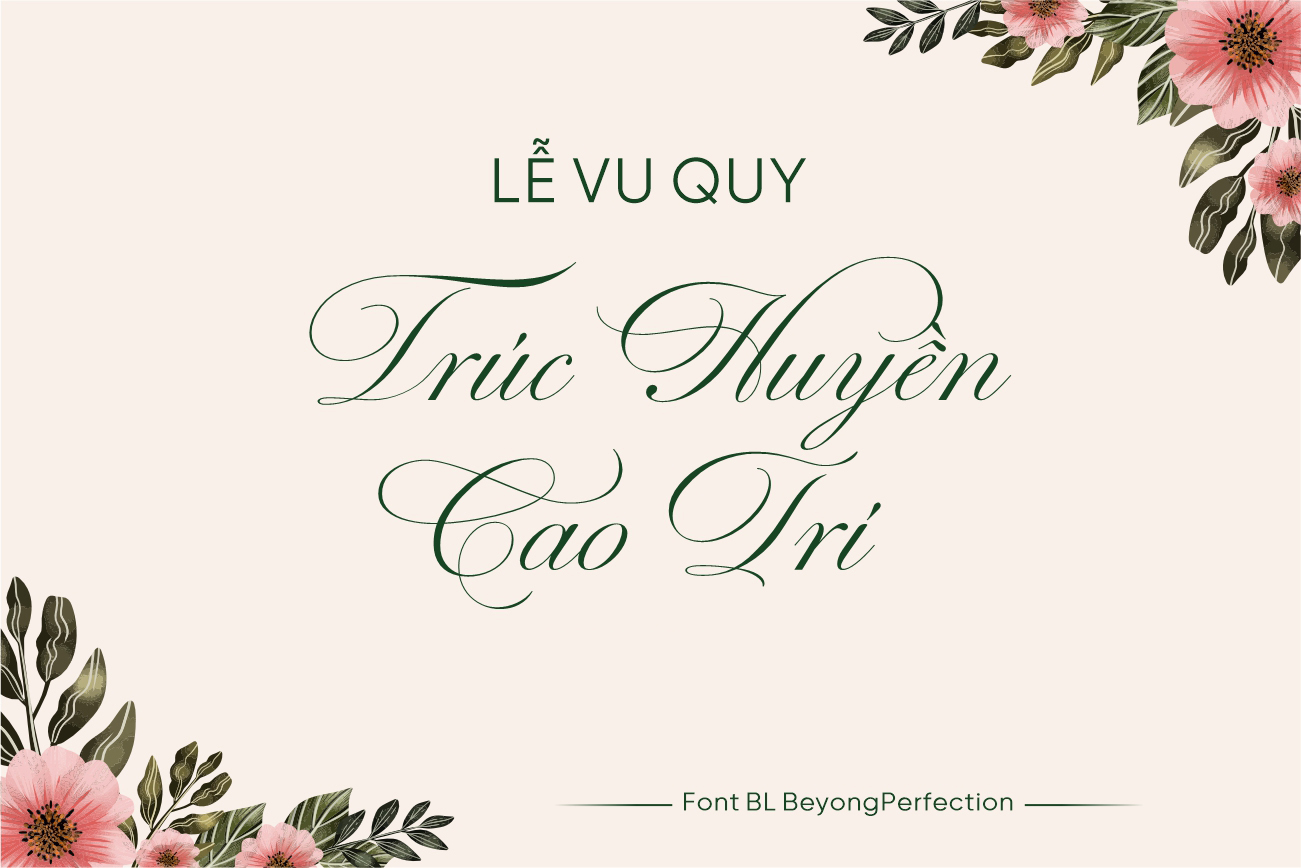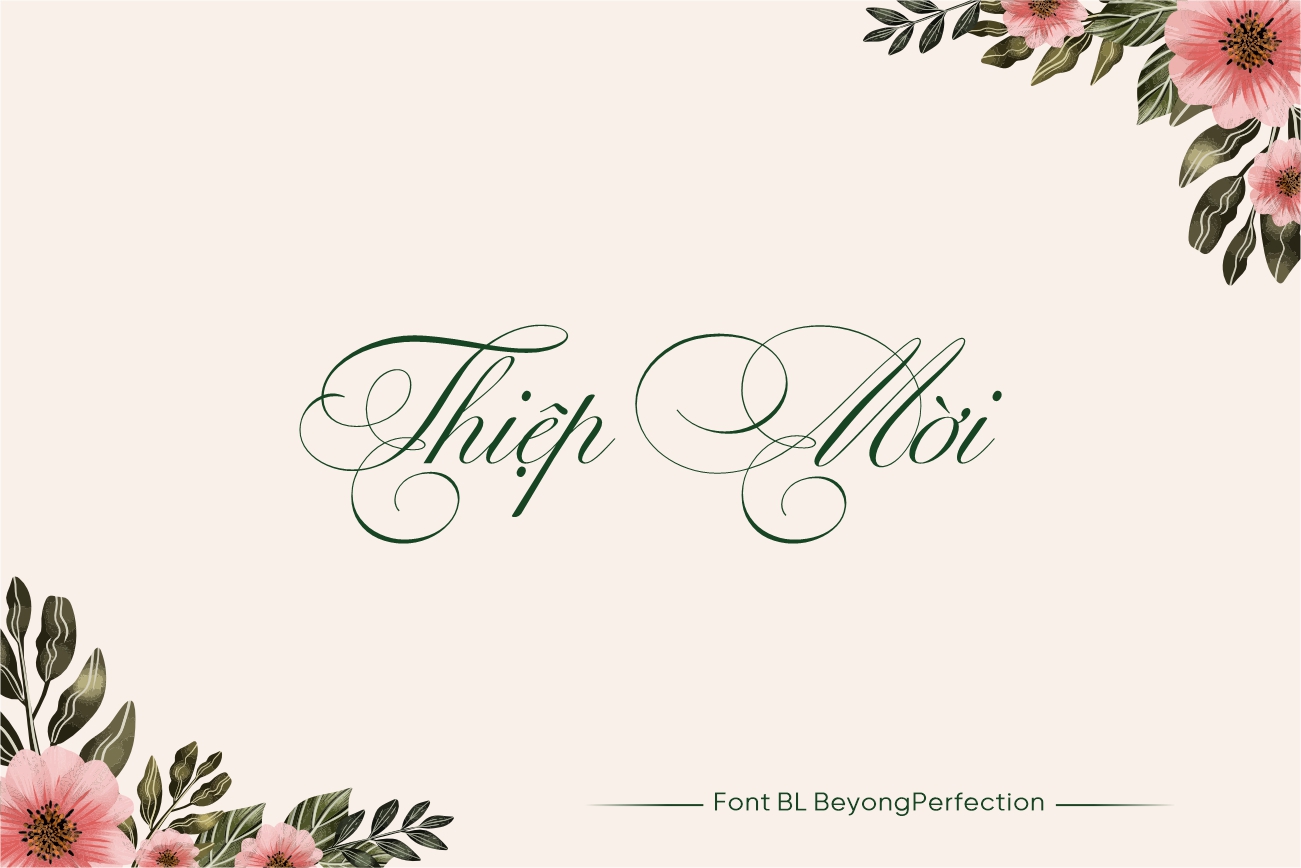
Phông chữ nét mảnh cho thiệp cưới BL Beyond Perfection Việt Hóa
BL Beyond Perfection là phiên bản Việt hóa từ bộ font Beyond Perfection do Hendra Pratama thiết kế, mang đậm tinh thần nghệ thuật của chữ viết tay cao cấp và cảm xúc lãng mạn. Ngay từ cái nhìn đầu tiên, bộ chữ tạo ấn tượng bởi sự mềm mại, uyển chuyển và tinh tế, thể hiện rõ nét của một font script hiện đại kết hợp calligraphy. Team BL đã Việt hóa cẩn thận, tối ưu hệ thống dấu tiếng Việt để từng ký tự liền mạch, hài hòa và giữ được trọn vẹn vẻ đẹp nguyên bản của font gốc. Nhờ đó, BL Beyond Perfection không chỉ đẹp về mặt thị giác mà còn dễ ứng dụng trong các dự án thiết kế tại Việt Nam.
Về kiểu dáng, BL Beyond Perfection sở hữu những đường nét uốn lượn tự nhiên, mềm mại và có nhịp điệu rõ ràng, tạo cảm giác uyển chuyển như bút mực đang lướt nhẹ trên giấy. Các nét chữ được xử lý với độ dày mỏng linh hoạt, mang lại chiều sâu và cảm xúc cho từng con chữ. Sự kết hợp giữa cấu trúc script hiện đại và tinh thần calligraphy cổ điển giúp font vừa mang hơi thở đương đại, vừa giữ được vẻ sang trọng và nghệ thuật. Khi sử dụng trong thiết kế, bộ chữ dễ dàng trở thành điểm nhấn, làm cho nội dung trở nên nổi bật mà không bị rối hay quá phô trương.
BL Beyond Perfection đặc biệt phù hợp với những thiết kế cần truyền tải cảm xúc và tính thẩm mỹ cao. Từ thiệp cưới, thiệp mời, thiệp chúc mừng, logo thương hiệu cá nhân, thời trang, mỹ phẩm cho đến poster nghệ thuật hay nội dung truyền thông trên mạng xã hội, font đều phát huy tốt khả năng gợi cảm xúc. Tổng thể kiểu chữ gợi cảm giác lãng mạn và nghệ thuật, giúp người xem cảm nhận được sự tinh tế, nhẹ nhàng và giàu chất thơ trong từng dòng chữ. Đây là lựa chọn lý tưởng cho những dự án cần sự mềm mại nhưng vẫn giữ được nét chuyên nghiệp và chỉn chu.
Nguồn gốc của Beyond Perfection xuất phát từ cảm hứng về sự hoàn mỹ trong nghệ thuật chữ viết tay, nơi từng chi tiết nhỏ đều góp phần tạo nên cảm xúc trọn vẹn. Khi được Team BL Việt hóa thành BL Beyond Perfection, bộ font không chỉ giữ nguyên tinh thần sáng tạo của Hendra Pratama mà còn trở nên gần gũi hơn với người dùng Việt. Nếu bạn đang tìm kiếm một font script hiện đại kết hợp calligraphy, có nét chữ uyển chuyển như bút mực, đồng thời gợi cảm giác lãng mạn và nghệ thuật, BL Beyond Perfection chắc chắn sẽ là lựa chọn giúp nâng tầm thẩm mỹ và tạo dấu ấn cảm xúc rõ rệt cho mọi dự án thiết kế.